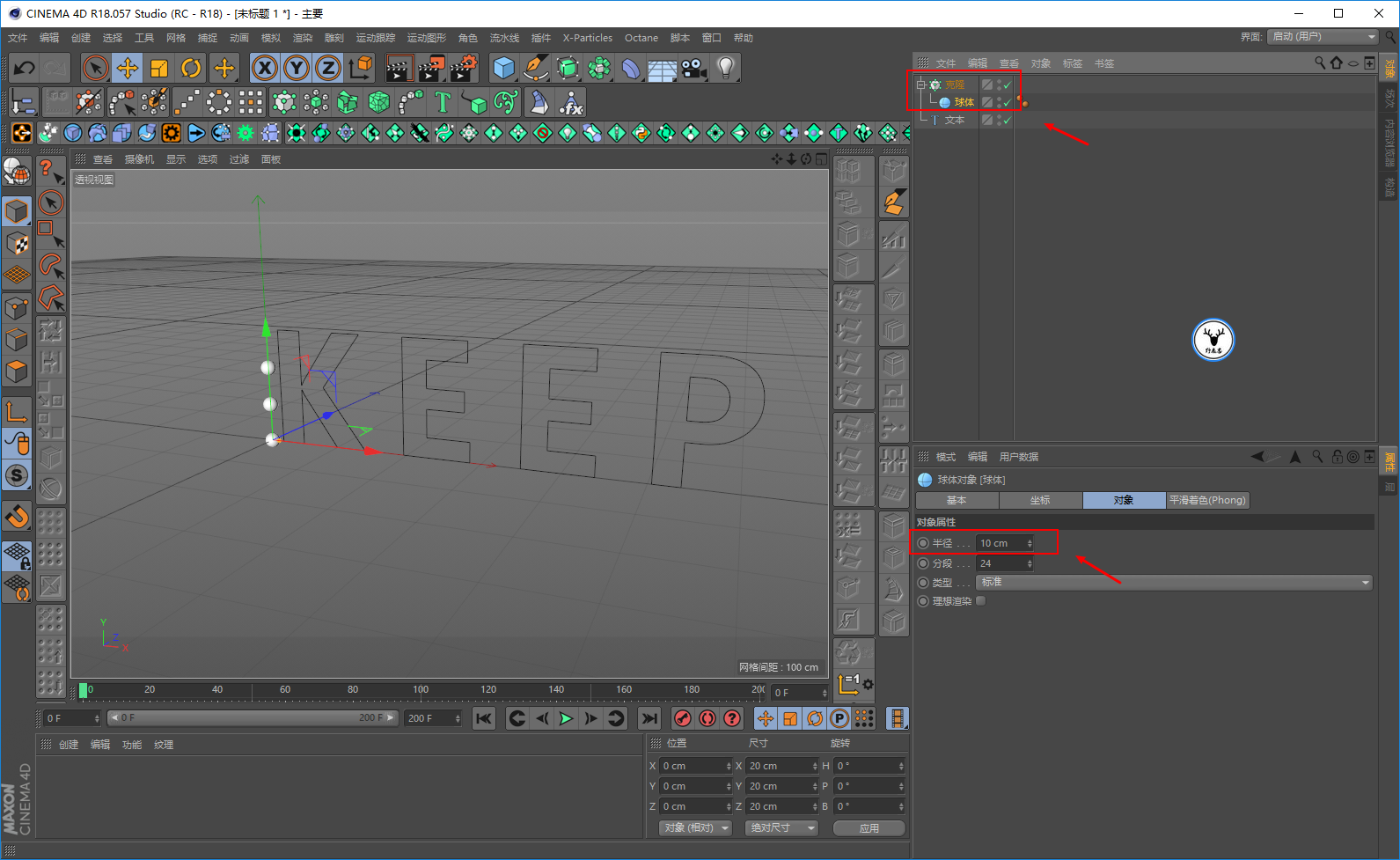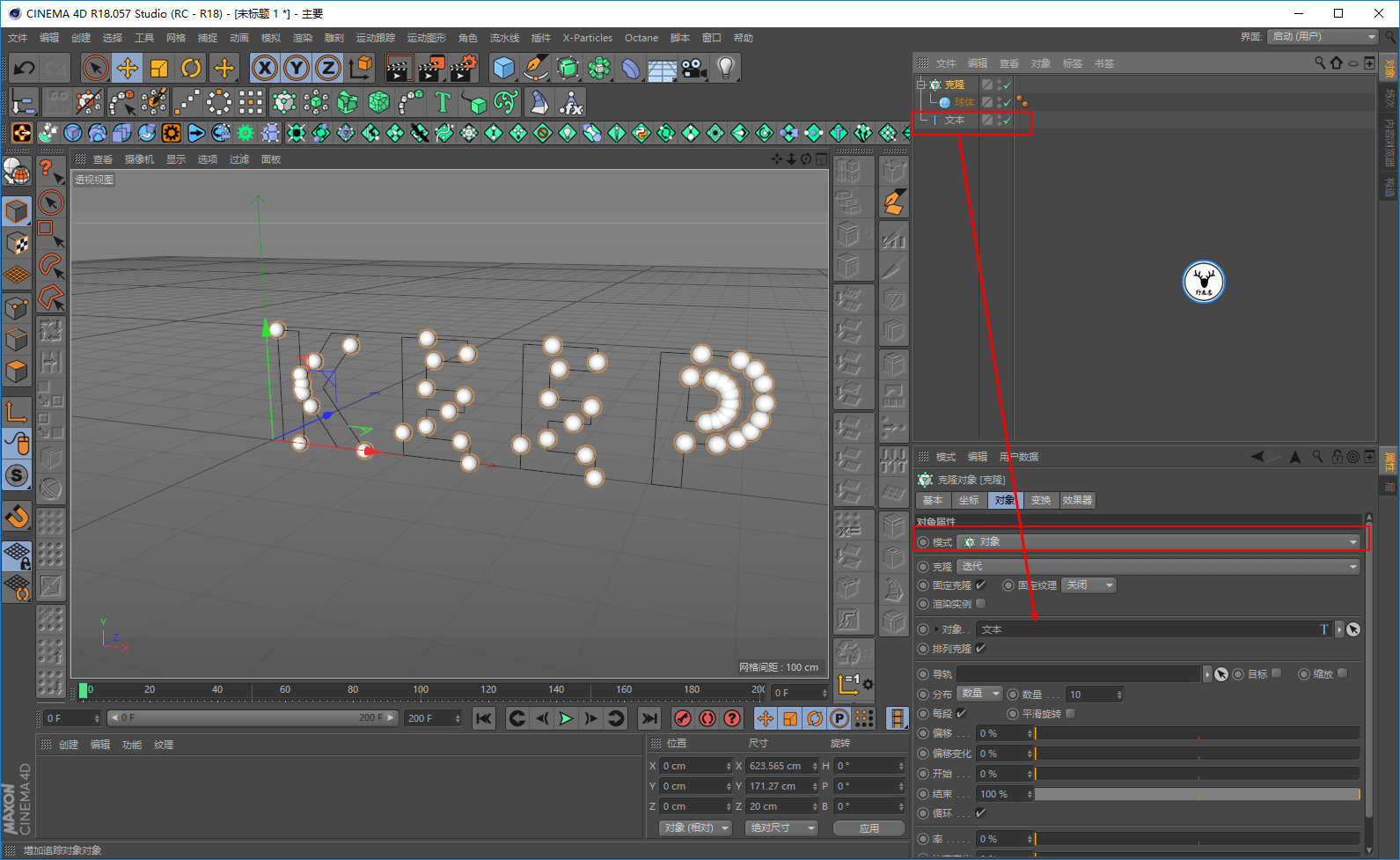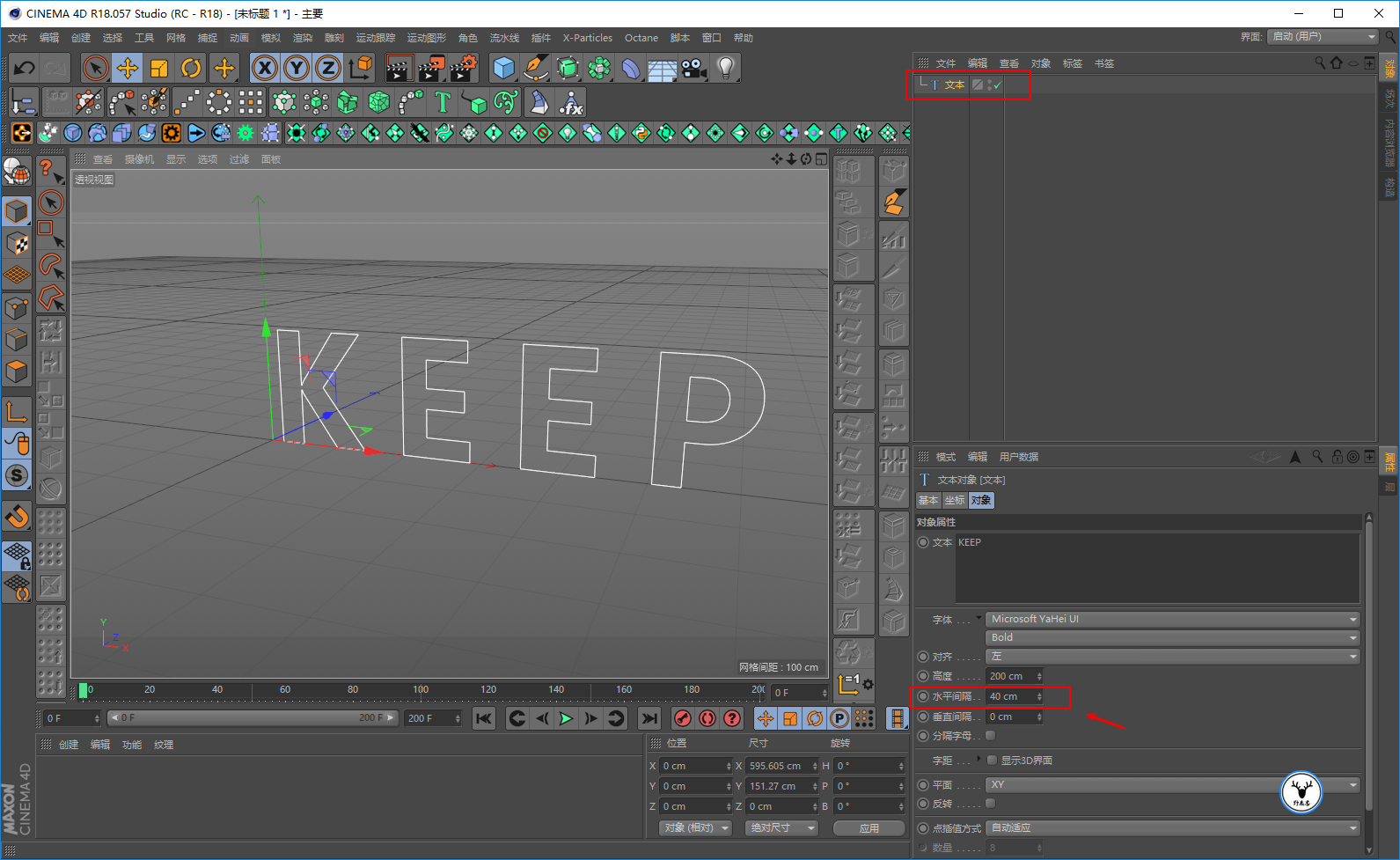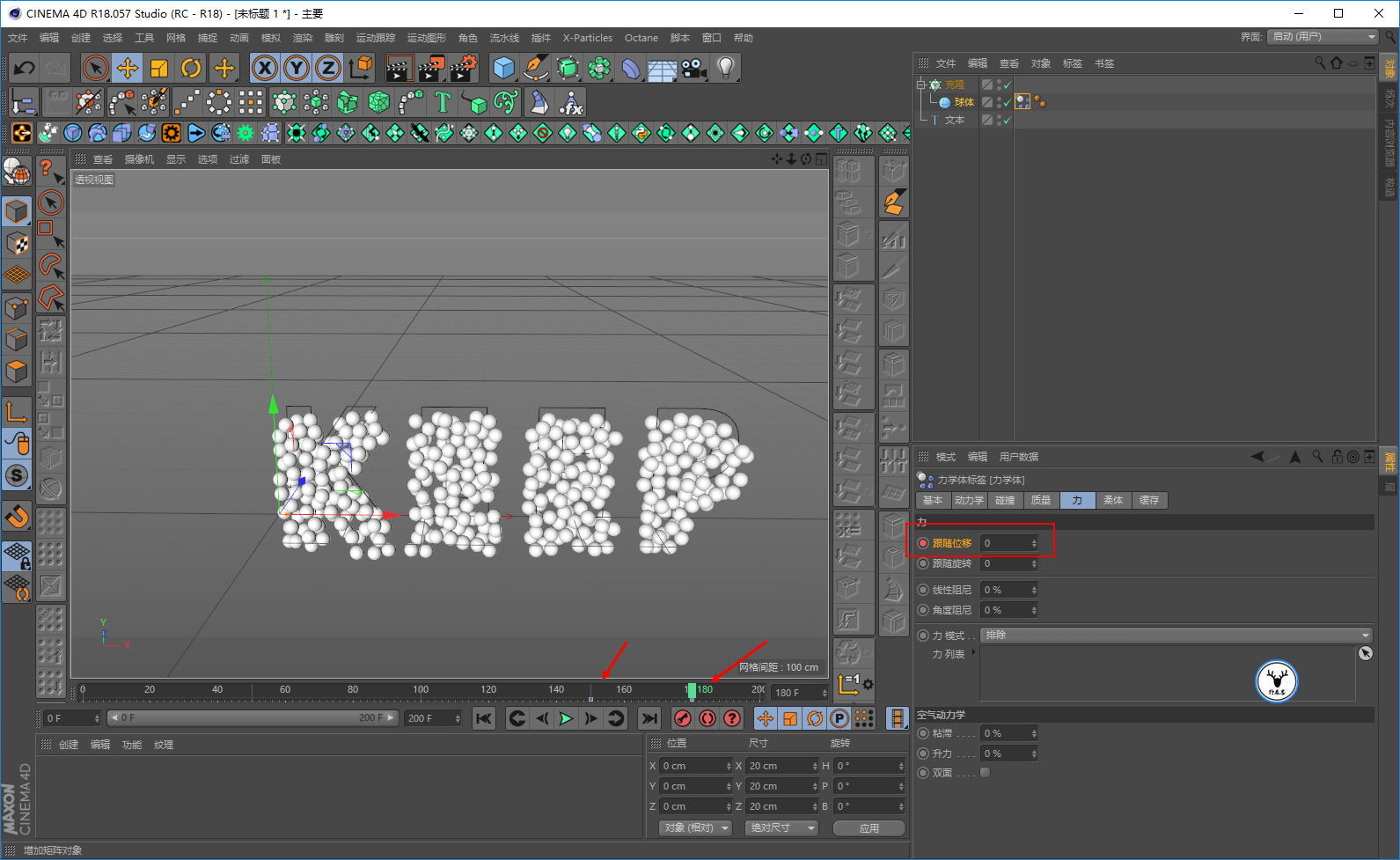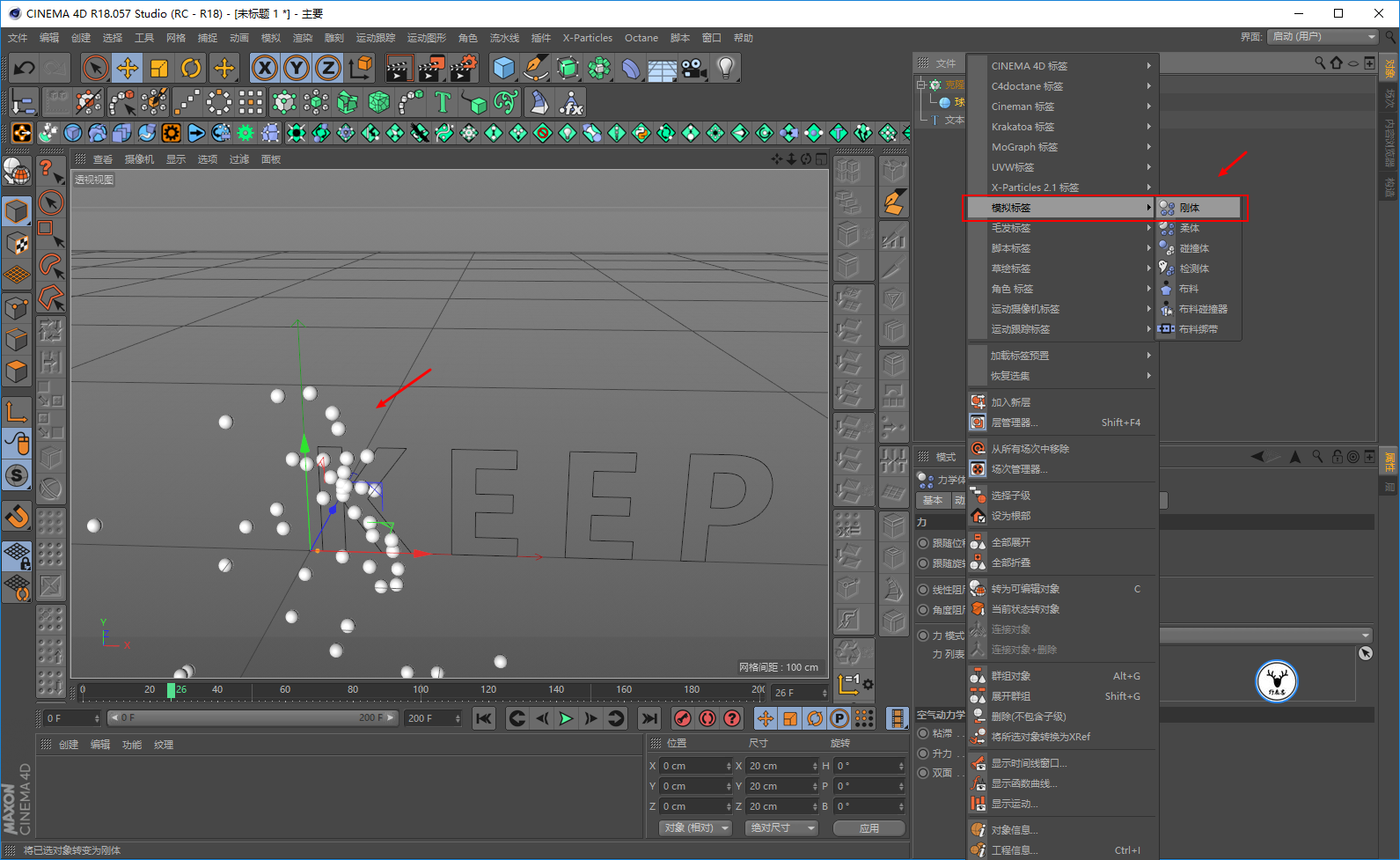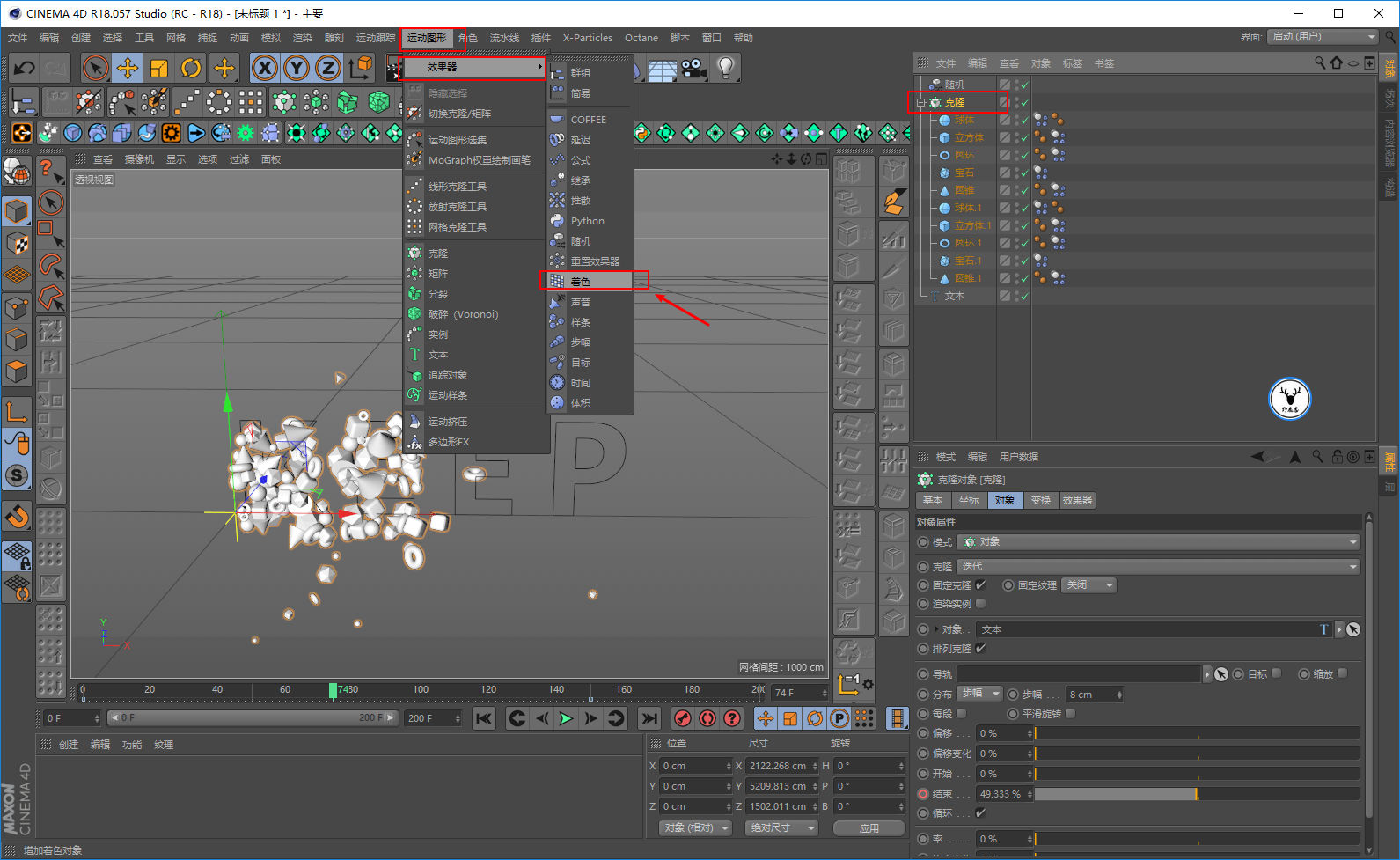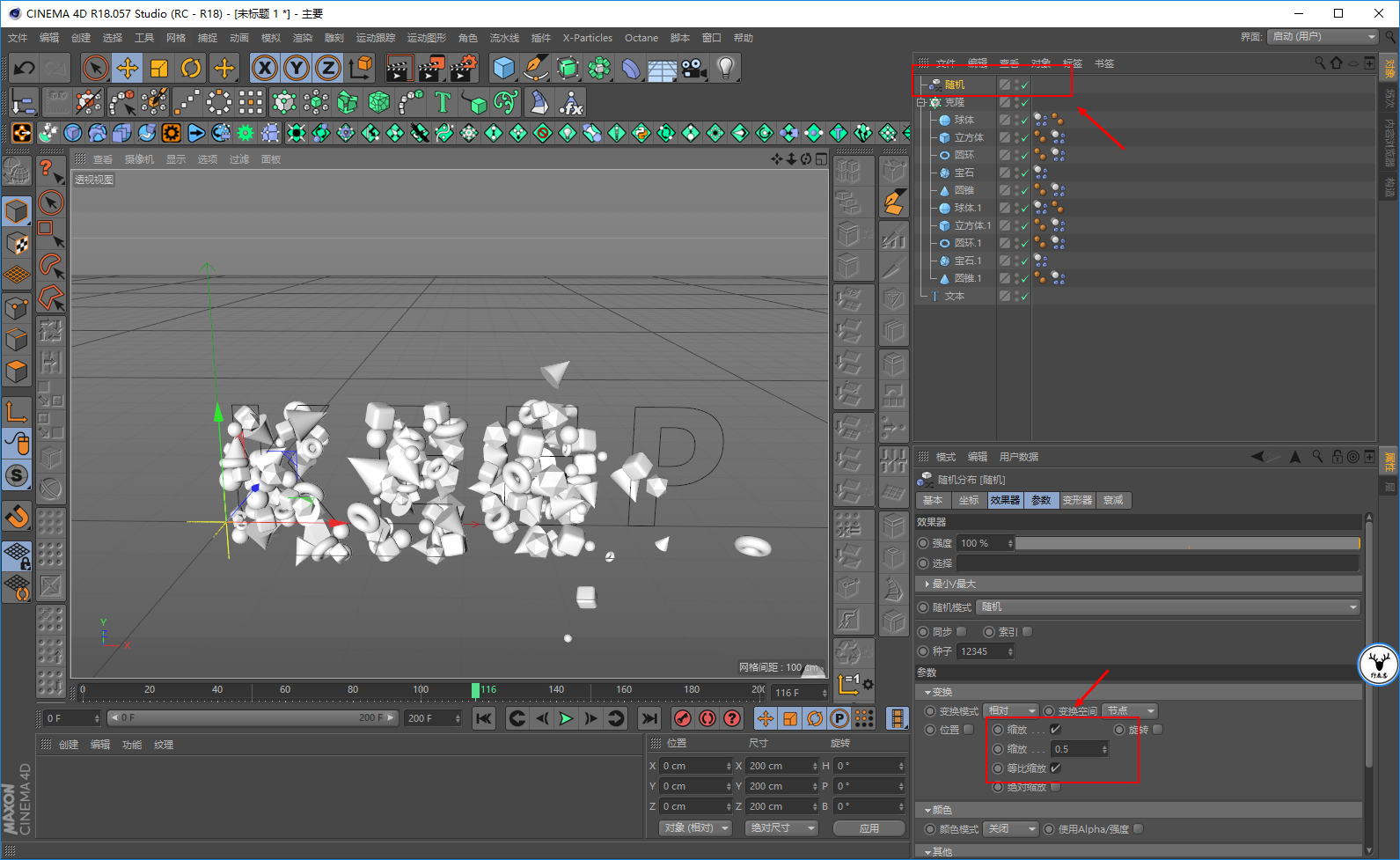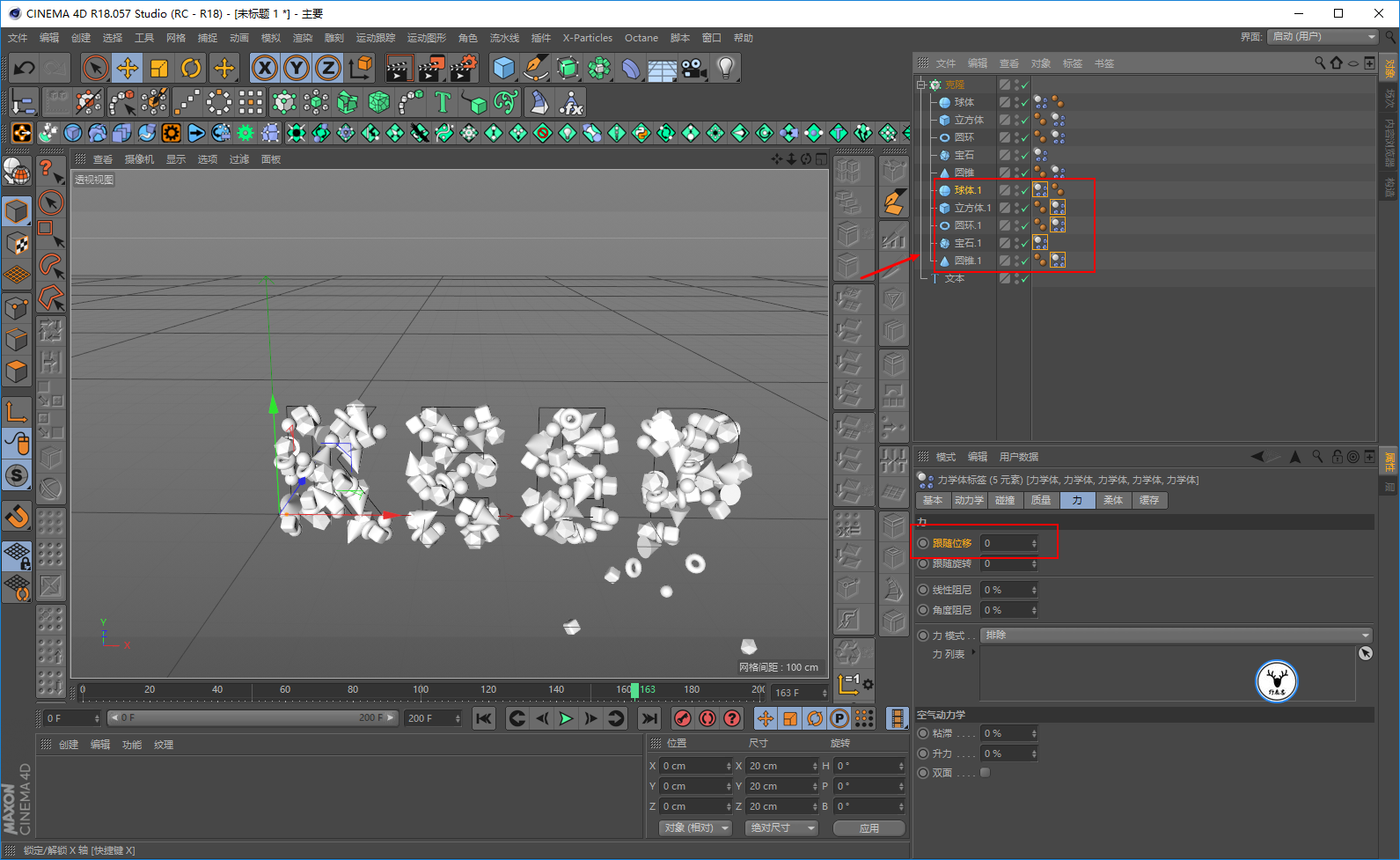
来制作放鞭炮一样的几何体文字动画吧!
这种类似像放鞭炮一样的文字动画效果,如果再配上一些节奏感强一点的BGM看来非常好玩。
我尝试了一下,其实动画部分并不是很难,主要是克隆再加上动力学的运用。
来吧,今天我们就来一起动手做一个像放鞭炮一样的几何体文字动画吧!
打开C4D,先把帧速率设置为25帧,我这里就做200帧的动画吧:
新建一个文本样条,选择一个粗一点的字体,文本的间距可以适当拉开一点:
新建克隆对象,新建一个球体适当的缩小球体的尺寸,让克隆对象克隆球体:
将克隆模式改为对象,以为文本样条作为对象来进行克隆:
将分布模式改为步幅,适当的缩小步幅的间距,把每段的勾去掉,这样我们在调整结束的参数的时候,小球就会从左到右的出现了:
这里就可以先做一个生长动画了,如图我在第0帧的时候结束的参数为0打上关键帧,然后到150帧的时候,结束参数为100打上关键帧:
再给球体添加模拟标签里的刚体,点击播放键会看到小球会自动的弹开:
没关系,我们只要适当的给跟随位移一点参数,这样小球就会尽量的保持字母的形态:
我这里希望的是当生长动画完毕时,小球会下落,所以在150的时候跟随位移的数值都是5打上关键帧,然后在180帧的时候,跟随位移的数值为0打上关键帧:
再添加几个几何体,直接把刚体标签复制给它们就行了,这一步不用多说吧。
但是这个时候你会发现动画里几何体并不会像鞭炮一样弹开:
没关系,我们再复制一些几何体出来,把他们的跟随位移都改成0就可以了:
当然你还可以添加一个随机效果器,去随机几何体的大小,基本上动画就做好了,不难吧:
下面就是上材质了,需要注意的是原图的几何体颜色一闪一闪的。
其实要实现这个效果也不难的,首先我们需要在选中克隆对象的前提下添加着色效果器:
这里我们让着色效果器只影响对象的颜色,不影响位置、缩放以及旋转,记得把使用Alpha强度的勾去掉:
我们在着色器面板添加一个渐变:
然后在渐变里修改自己想要的颜色,只需要适当的调整湍流以及频率的数值,播放动画的时候,对象的颜色就是一闪一闪的了:
但是只是这样的话还不够好,因为仅仅通过着色效果器添加的颜色,对象不会有反射或者发光一类的信息:
所以这里我们需要新建一个材质球,把它丢给克隆对象,你会发现材质球的颜色会覆盖掉着色效果器的颜色。然后在颜色通道添加一个颜色着色器:
这个时候对象就既会使用着色效果器的颜色,并且也可以通过材质球来调整它的反射等信息。
反射通道的参数我这里就不写了,因为参数不重要,大家知道方法就好,做出自己觉得好的参数吧:
我个人觉得在发光通道也添加一个颜色着色器会比较好看一点,这个看个人吧,你不喜欢也可以不加:
新建一个大大的平面,给平面添加模拟标签碰撞体,这一步也不用说吧:
给平面添加一个黑色的反射材质,同样参数看着效果来就好:
新建一个天空和材质球,材质球只勾选发光通道,贴一张HDR贴图上去,把材质球赋予天空让它作为环境光:
给天空添加合成标签,把摄像机可见勾选掉,同时让天空排除地面,这样天空就只是作为一个环境照明并且只会对主物体产生反射:
佛系的打几盏灯吧,灯光里同样排除地面:
可以在不同的角度添加摄像机做一些镜头切换:
渲染设置里我开启了全局光照和环境吸收,全局光照的品质可以选择高一点:
渲染器选择物理渲染器,采用品质中等,这样的话噪点会比较少一点,不过也会增加渲染时长:
保存的设置记得把帧速率也改为25,然后渲染全部帧:
最后渲染出图导入pr加点文字和BGM看看效果吧:
啊啊啊,好像几何体可以再小一点,有点影响辨识度,不过老实说这个渲染的时间蛮久的: